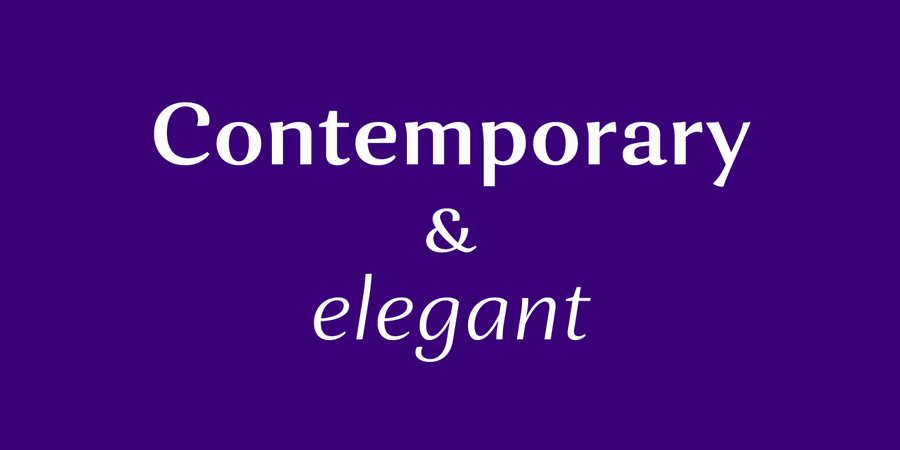
Orchidea Pro – це шрифт, що балансує на межі між гротеском та антиквою. Так звана стрічкова антиква або антиква-гротеск, шрифт не має жодних зарубок, але нагадує антикву за конструкцією та має односпрямовані закінчення, які прискорюють читання та створюють особливе розрізнення форми.
Таке рішення створює сучасний, але елегантний шрифт, практично унікальний за текстурою, який існує у єдиному стилістичному просторі зі шрифтами з плавними зарубками.
Orchidea Pro особливо добре підходить для використання у журналах, а також у брендінгу косметичних продуктів.
Шрифт має 8 варіантів насиченості від надтонкого до наджирного + відповідний справжній курсив. Кожне накреслення підтримує численні мови на латиниці, основні кириличні мови та містить безліч опен-тайп фіч: лігатури, капітель, 5 наборів цифр, 4 стилістичні набори у прямих накресленнях та 1 у курсивном, дроби, індекси, різні знаки пунктуації, включно з пунктуацією для капітального складання, а також мовні альтернативи.
Шрифт Orchidea Pro розробив і випустив Андрій Константинов у студії Mint Type у 2017 році.